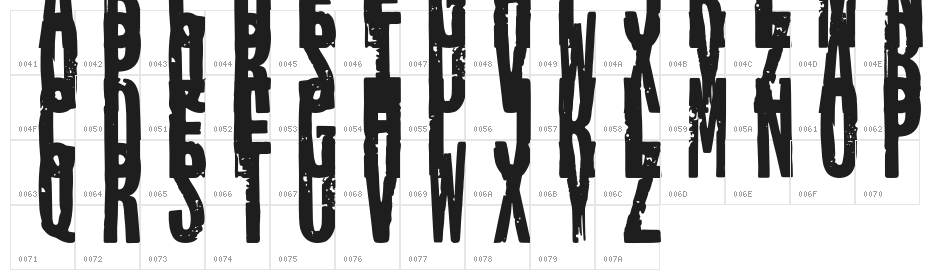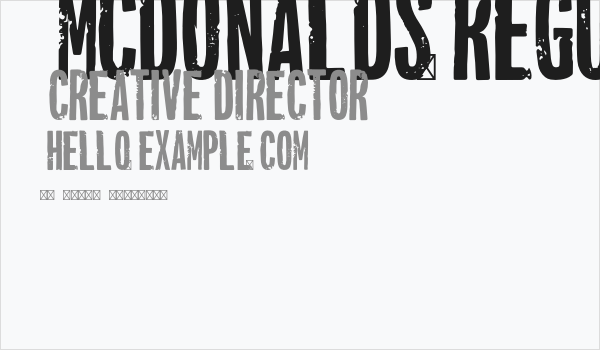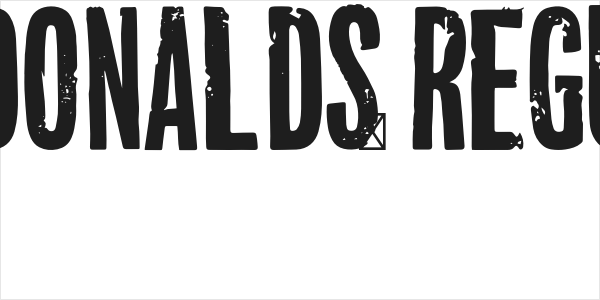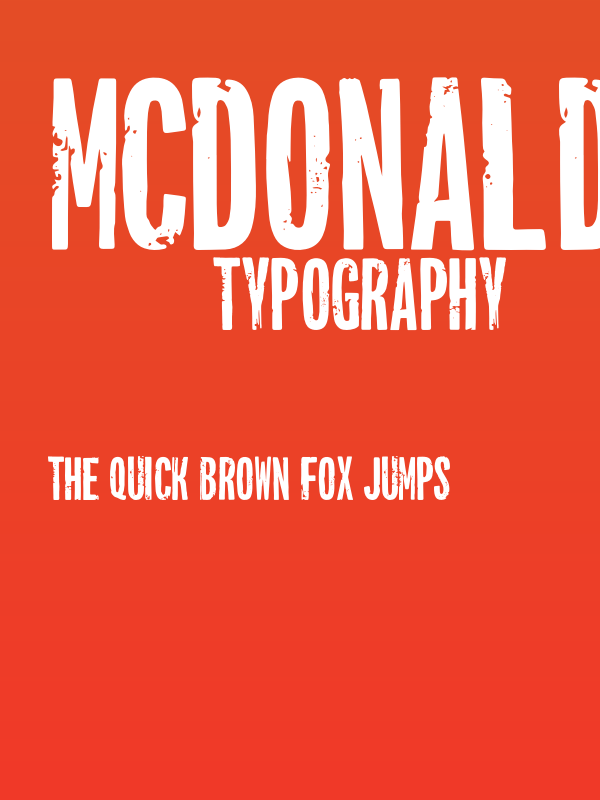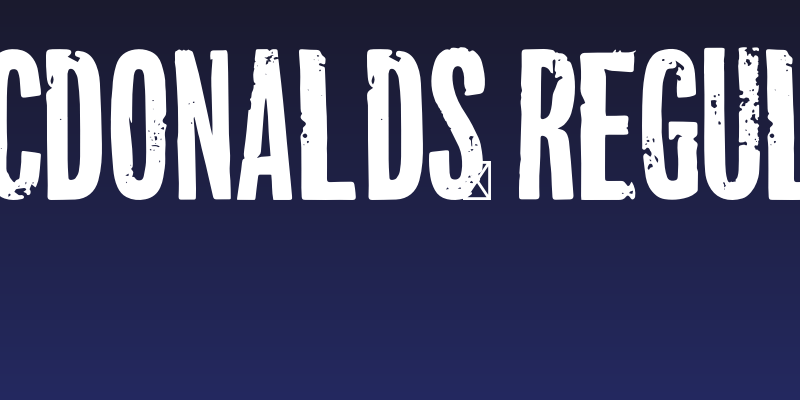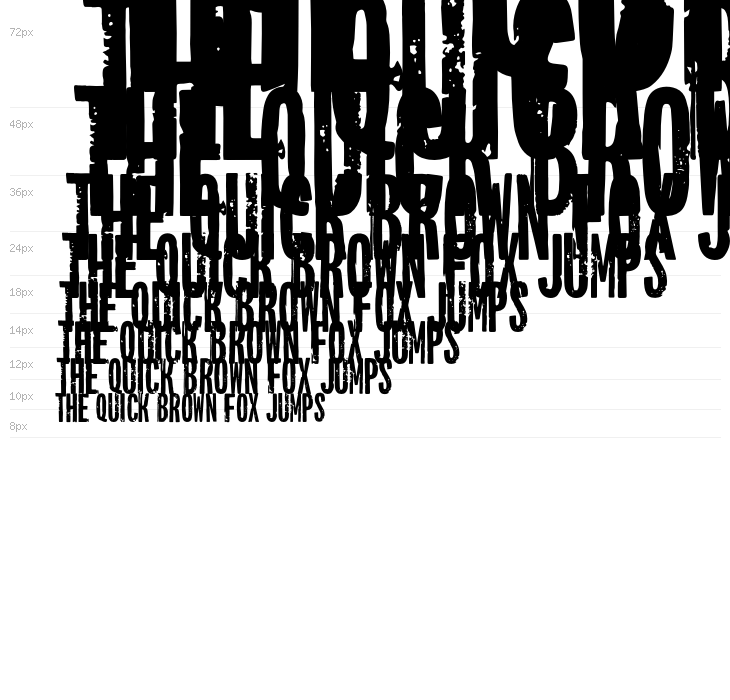
McDonalds-Regular Font
✎ Distorted Eroded
| Gesamtstil | Grunge, Urban, Edgy |
| Vorgeschlagene Projekte | Ideal for music album covers, event posters, streetwear branding, or any project needing an edgy, urban vibe. |